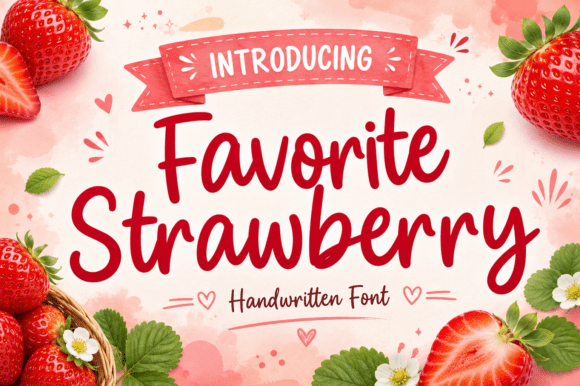
Favorite Strawberry
หากคุณกำลังมองหาเนื้อหาคุณภาพสูงเช่น Favorite Strawberry แพ็คเกจพรีเมียมนี้เป็นตัวเลือกที่ยอดเยี่ยมสำหรับโปรเจ็กต์สร้างสรรค์ของคุณ
ไม่ว่าคุณจะสร้างผลิตภัณฑ์ POD (Print on Demand) คำเชิญงานแต่งงาน หรือกราฟิกโซเชียลมีเดีย Favorite Strawberry ก็เหมาะสมอย่างยิ่ง